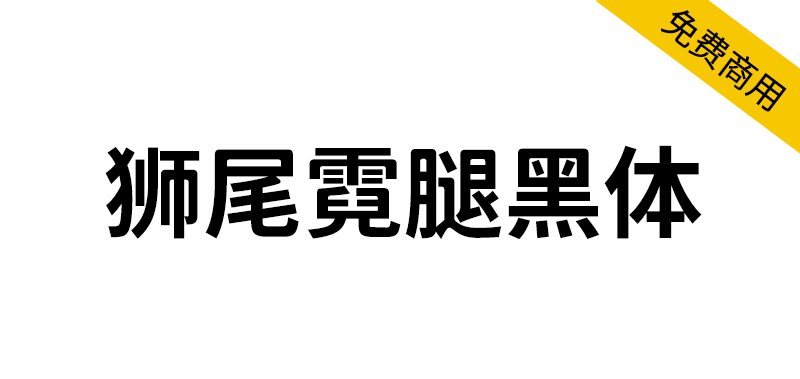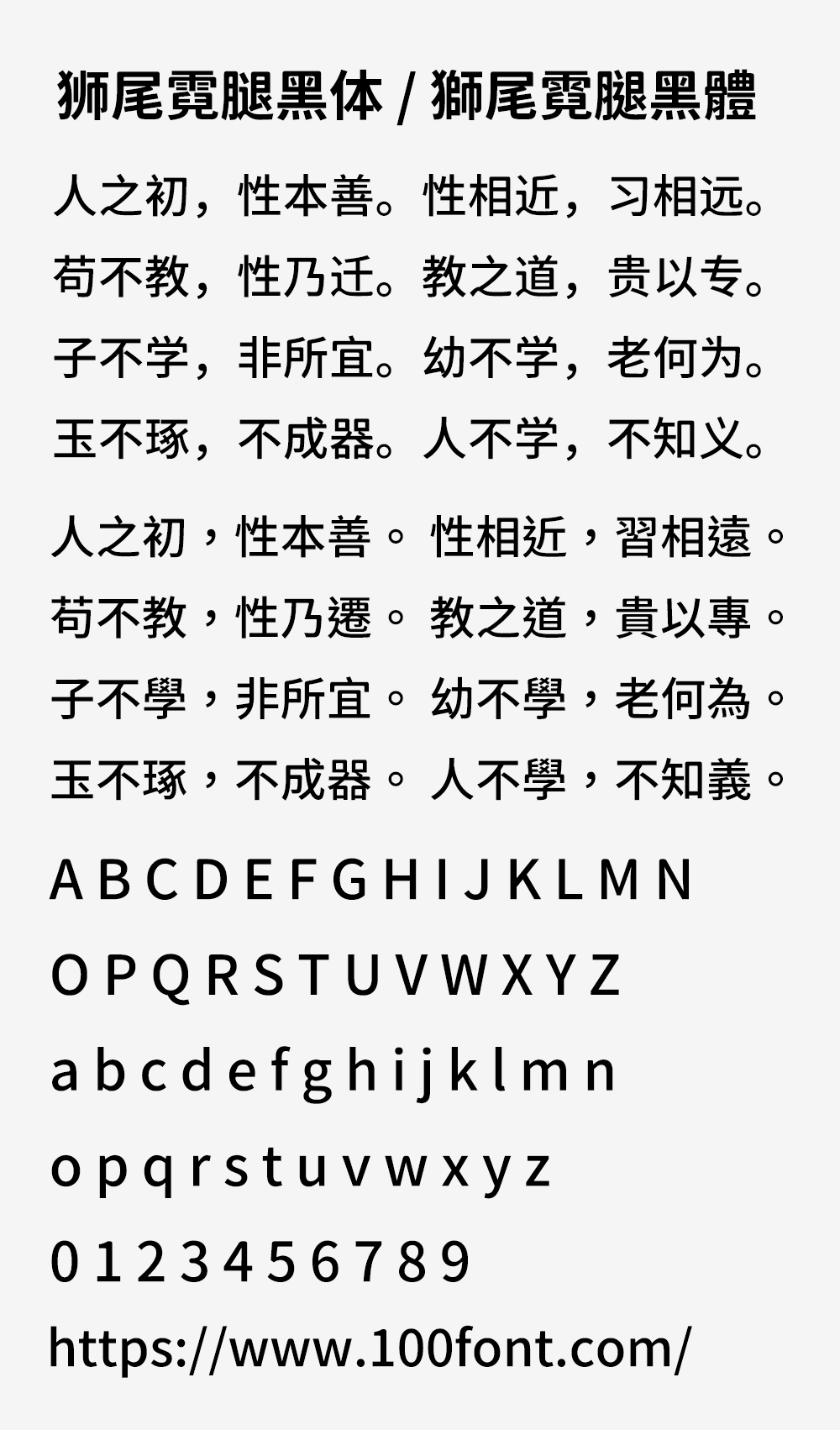
狮尾霓腿黑体基于思源黑体的上半边变圆改造,更加简明现代化的字体。狮尾霓腿黑体的特色是上半边圆体+下半边黑体,一个综合的字体,「口」字的上沿有一点点像彩虹形状。和思源黑体一样,有7种字重,支持简体中文、繁体中文、韩文与日文,可以免费商用,欢迎大家自由应用、自由优化、自由改作!
狮尾霓腿黑体与「狮尾彩虹腿」的主要差别在笔触是否有做调整,霓腿所套用的效果较少,在笔触没有做调整。
狮尾霓腿黑体与「狮尾霓黑体」差别在有没有拔脚,「拔脚」就是会有较少的笔画,例如移除「口」字的左右下角会多出的短线条。有拔脚的字会较圆,但是会造成有些字因直接去掉腿后左右不平衡、左右不对衬的「悬空」问题。改使用「腿」系列字体就不会有这个问题。